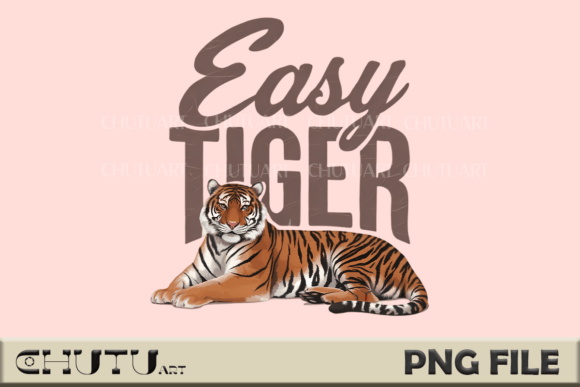
Easy Tiger - Wild & Relaxed Aesthetic
Conçu avec précision, Easy Tiger - Wild & Relaxed Aesthetic offre des vecteurs nets, une typographie fluide et une licence commerciale pour une tranquillité d'esprit.